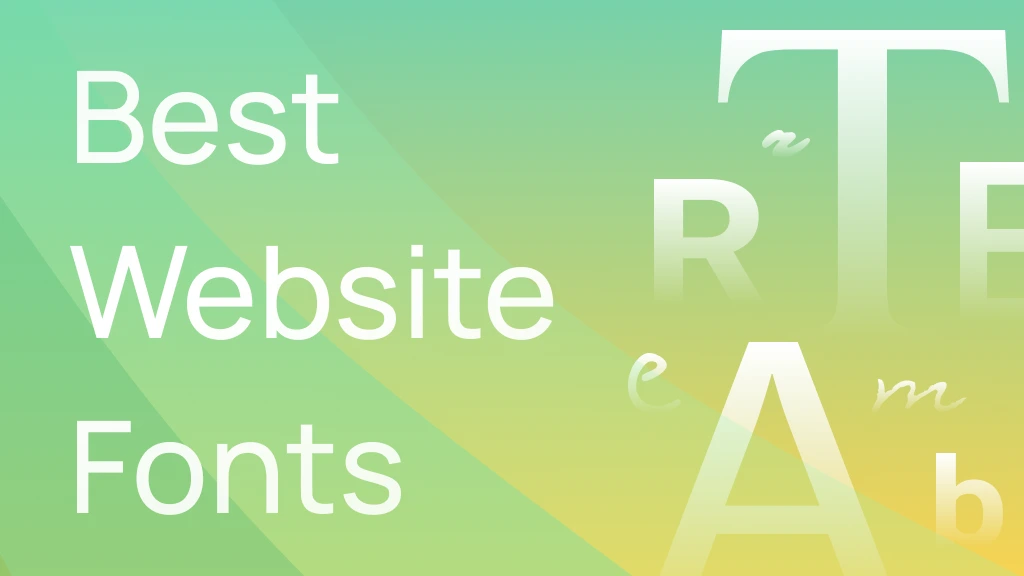
51+ лучших шрифтов для веб-сайтов
Вы ищете идеальный веб-шрифт для своего сайта? У вас есть уникальная отрасль, которая нуждается в характерном шрифте? А может и наоборот - ваш сайт должен быть элегантным и профессиональным, поэтому шрифт, прежде всего, должен быть читабельным. Вне зависимости от того, какая ситуация представляется вам лучше — в этом списке вы найдете шрифт на любой случай. Не ждите, найдите лучшый шрифт для вашего сайта прямо сейчас!
Выбор вашего веб-шрифта
Типографика является важным элементом дизайна и коммуникации , который влияет на то, как посетители воспринимают веб-сайт, бренд или человека, которому он принадлежит.
Ключ к успеху в том, чтобы каждый элемент дизайна сайта был последовательным и создавал гармоничную композицию. Правильно подобранный шрифт может многое рассказать о характере бренда, о том, что он хочет донести до своих получателей и какие ценности им движут. С другой стороны, неправильно выбранный шрифт может плохо отражать характер бренда, вводить пользователей в заблуждение и создавать неадекватные ожидания.
Список лучших веб-шрифтов на все случаи жизни
Ниже вы найдете список лучших шрифтов, соответствующих конкретным обстоятельствам. Прежде чем выбрать шрифт, подумайте о том, что вы хотите передать и как вы хотите, чтобы вас воспринимала аудитория, которая будет идентифицировать шрифт с вами или вашим брендом. Когда ваши цели четко определены, выбор идеального шрифта не доставит вам никаких проблем!
Универсальные шрифты
Как распознать универсальные шрифты? Во-первых, они вам знакомы, потому что вы видите их каждый день. Вы, несомненно, знаете такие названия, как Helvetica или Arial. Это универсальные шрифты!
Универсальные шрифты должны хорошо смотреться любого размера, на любом портативном носителе (бумаге или экране компьютера) и в любом проекте. Типичной особенностью универсальных шрифтов является то, что они имеют различные диакритические знаки. Однако нет никакой гарантии, что интересующий вас шрифт будет содержать нужные вам специальные символы! Поэтому перед выбором шрифта обязательно убедитесь, что он поддерживает все необходимые языки!
Универсальные шрифты обычно используются на всех видах веб-сайтов и их контента, целевых страницах, статьях в блогах, в более длинных формах, таких как электронные книги или документы, интернет-магазины, приложения и многие другие. Если вы хотите, чтобы ваше коммуникация была безопасной, сдержанной и не вычурной, выберите универсальный шрифт.
→ Стиль: ясный, профессиональный, минималистский, элегантный - старая, добрая классика!
Это простой универсальный шрифт, созданный польским дизайнером Лукашем Дзедзичем. Его можно с успехом использовать в самых разных проектах. Lato — классический шрифт, который будет работать на большинстве веб-сайтов, лендингах, резюме или портфолио. Он подчеркивает профессиональный характер каждого проекта и чрезвычайно легко читается.
→ Стиль: четкий, профессиональный, минималистичный и современный
Roboto — простой, но современный шрифт, разработанный Кристианом Робертсоном. Приятно читать и хорошо смотрится как в тонкой версии, так и в полужирной или жирной.
→ Стиль: легко читаемый, простой, современный и минималистичный.
Это очень минималистичный шрифт. Он не имеет лишних украшений и держится в простой форме. Это хорошо работает для небольших и более значимых текстов. Его можно сочетать с более декоративным шрифтом в заголовках и названиях.
→ Стиль: простой, минималистичный
Это простой шрифт с историей. Первоначально разработан в 1957 году Максом Мидингером. В настоящее время это один из самых популярных шрифтов, который вдохновил многих на создание новых шрифтов. Благодаря своей нейтральности он вписывается в любой контент.
→ Стиль: элегантный, классический и профессиональный
Этот шрифт очень хорошо сочетает в себе современность и прошлое. Впервые он был использован в 1932 году в The Times of London и с тех пор ассоциируется с этой индустрией. Он идеально подходит для книг, газет или различных типов официальных документов. Однако не используйте его чрезмерно на веб-страницах, так как он немного устарел и может быть нечитаемым на экране. Исключением могут быть страницы новостных служб типа «Нью-Йорк Таймс».
Простые и минималистичные шрифты
Если вы хотите, чтобы создаваемый вами контент имел элегантный и слегка дизайнерский характер, стоит использовать минималистичные шрифты. Как правило, они не имеют никаких украшений. Как и универсальные шрифты, минималистичные шрифты должны легко читаться в любой форме и иметь все необходимые диакритические знаки.